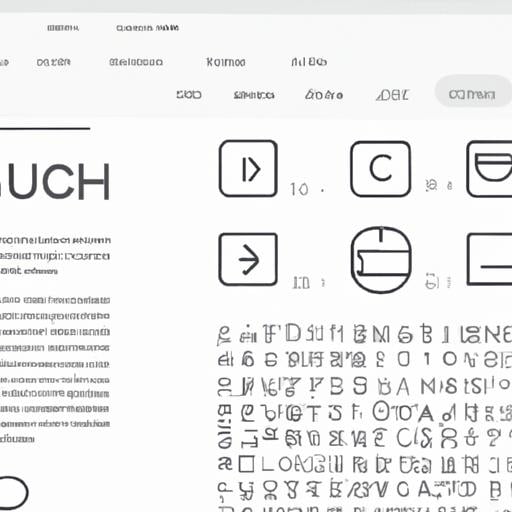
Font Chữ Font Simple Line Icons
Tác giả: Sabbir Ahmed
Ngôn ngữ: Hỗ trợ nhiều ngôn ngữ
Bộ Font: Simple Line Icons
Phân loại: Đơn giản, cơ bản
Kiểu chữ: Không chân
Font Simple Line Icons là một bộ font icon line độc đáo và hiện đại, được thiết kế để mang lại sự đơn giản và tinh tế cho các dự án thiết kế của bạn. Bộ font này bao gồm hàng trăm biểu tượng được vẽ bằng các đường nét mảnh mai, giúp tạo nên vẻ đẹp simple icon nhưng không kém phần chuyên nghiệp. Bạn có thể dễ dàng sử dụng simple to use icon trong các dự án website, ứng dụng di động, hoặc bất kỳ sản phẩm thiết kế nào cần đến sự gọn gàng và thanh lịch. Với font icon line, mỗi biểu tượng đều mang lại cảm giác tươi mới và tối giản, làm nổi bật nội dung của bạn một cách tự nhiên và dễ dàng.
Ảnh demo font chữ Simple Line Icons
Dưới đây là một số ảnh demo font chữ Simple Line Icons: